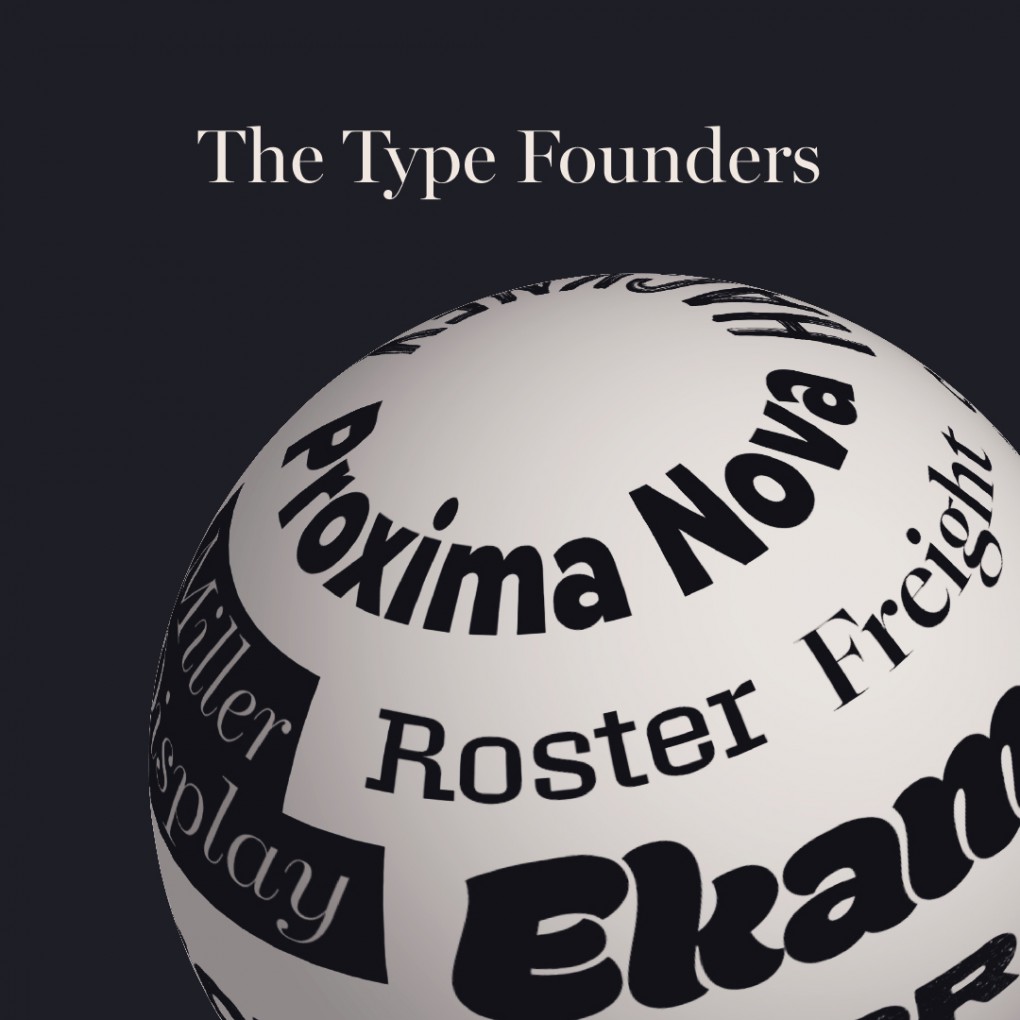
큰 거 왔다..!! 무려 4,400여종 폰트의 주인공, 바로 더타입파운더스(TTF) 입니다.
산돌구름이 국내 폰트 플랫폼 최초로 더타입파운더스(TTF)와 입점 계약을 체결했습니다. 2023년 8월 796패밀리 4,443종 폰트 출시를 시작으로, 향후 약 6,500여종 이상의 폰트를 순차적으로 선보일 예정이에요. 당연하게도, 해당 폰트들은 사용 범위 제한 없이 자유롭게 이용 가능합니다.
더타입파운더스(TTF), 맥도날드·킨더 등 글로벌 브랜드들이 선택한 폰트가 가득!
「Proxima Nova」, 이미 너무나 유명한 폰트죠?
더타입파운더스(TTF)는 미국, 브라질, 영국, 포르투갈 등 25개 이상 브랜드와 6,500종이 넘는 폰트를 보유한 세계적인 폰트 파운더리로, 「Proxima Nova」를 포함해 맥도날드 패키지에 사용된 「Populaire」, 애니메이션 ‘파워퍼프걸’ 자막에 활용된 「Unpack」, 킨더 홈페이지 제작에 사용된 「Chronic」, 네스퀵 패키지에 적용된 「Daft Brush」, 스타벅스 메뉴판에 쓰인 「Likely」, 돌(Dole)의 라벨 디자인에 적용된 「Thirsty Rough」 등 셀 수 없이 다양한 글로벌 유명 브랜드사의 사용 사례가 넘쳐난답니다.